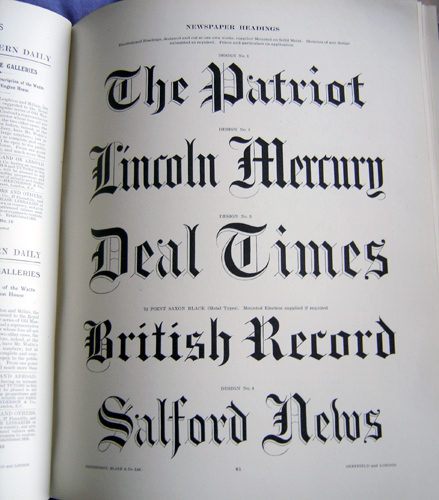
Suche Schrift ähnlich Old English EF Regular
Ist das aus einem Zeitungskopf? Falls ja, könnte es helfen, wenn Du uns sagst aus welchem. Die Chancen stehen allerdings dafür, dass das handgezeichnet ist. Aus dem Kopf kann ich nur sagen, dass Du mit der Fetten Kanzlei Fraktur ein gutes Stück näher dran sein dürftest als mit der Old(e) English.
Ansonsten solltest Du mal die gängigen Anbieter gebrochener Schriften angucken.
Die Schrift hab ich von einer alten Zeitung, vermutlich "The Times", bin mir aber nicht sicher, da ich nur noch einen Teil habe.
Zumindest ist es nicht die englische The Times (die benutzt nämlich die nach ihr benannte Schrift im Titel, früher TNR, heute Times Modern), auch die New York Times und die Las Angeles Times benutzen andere gebrochene Schriften.
Versuch doch mal dies für den Anfang ...
Danke, aber die andere oben gefällt mir dann doch besser. Ich werde versuchen, ob ich doch noch irgendwie die "times old roman" finde.